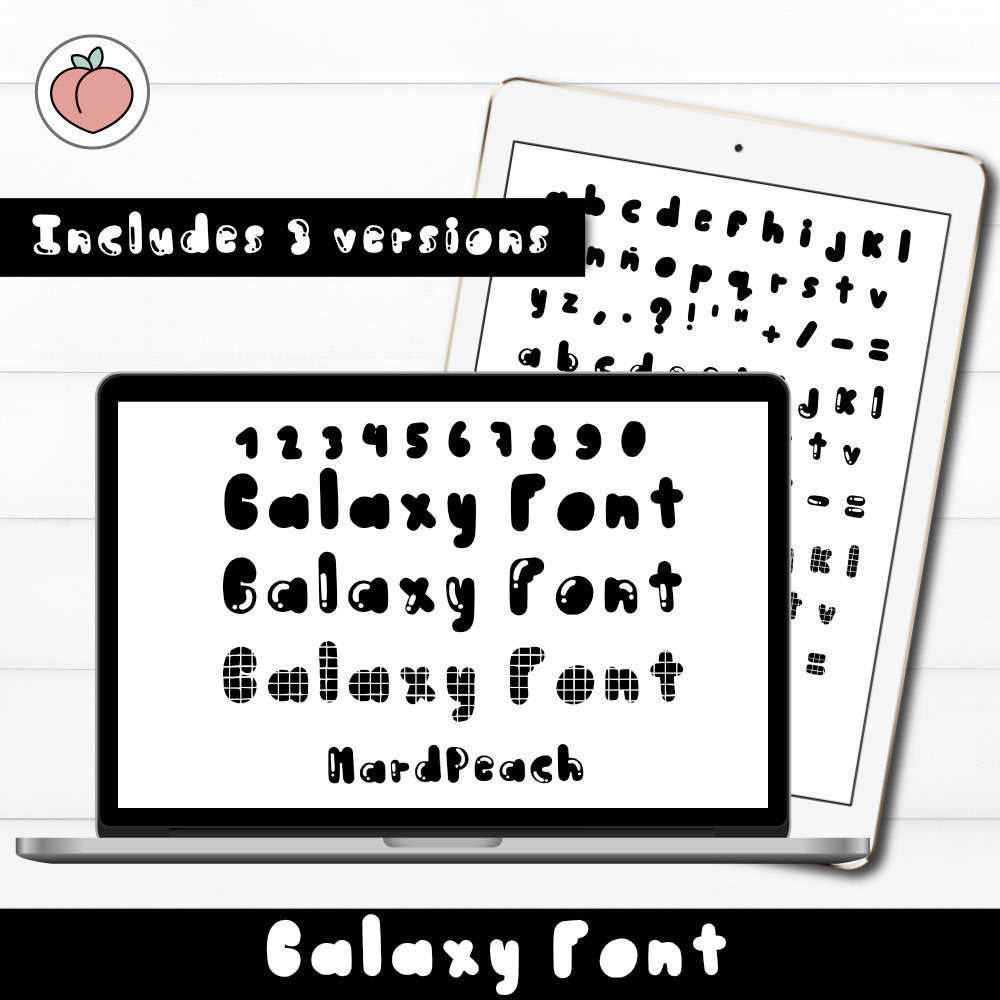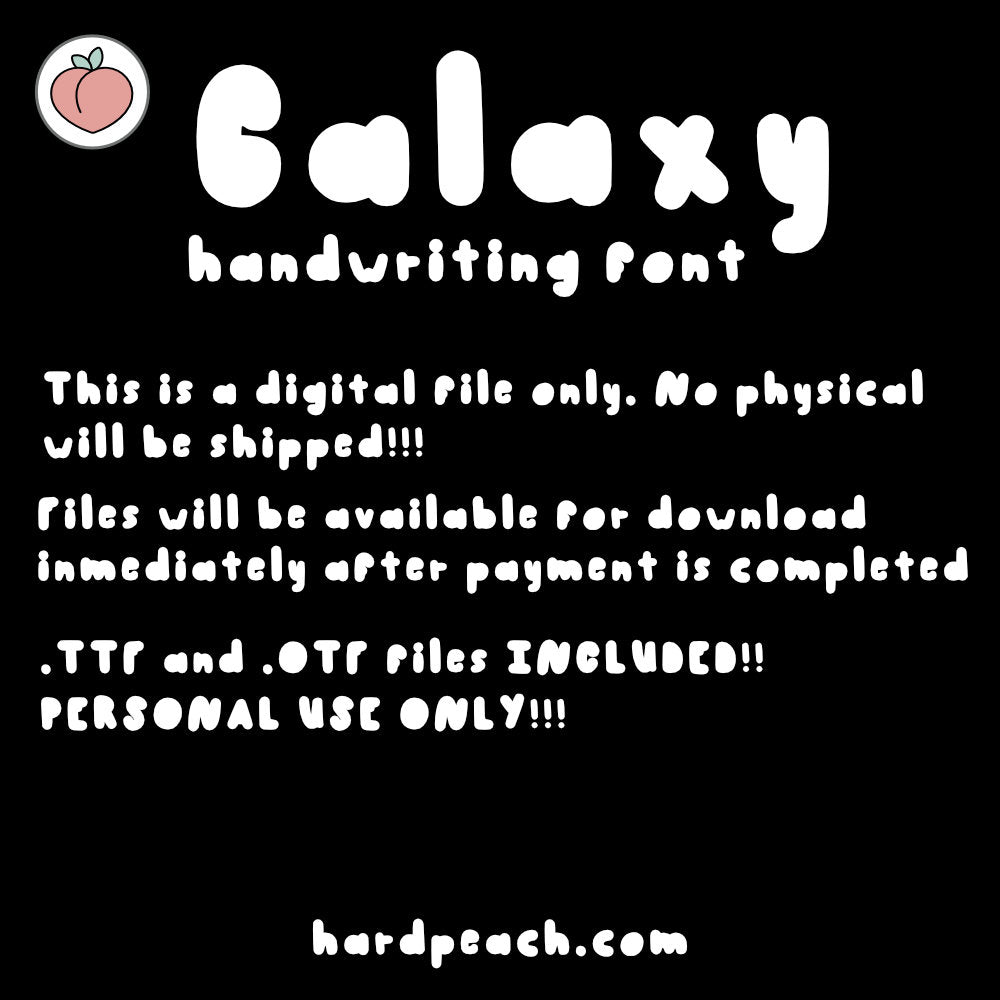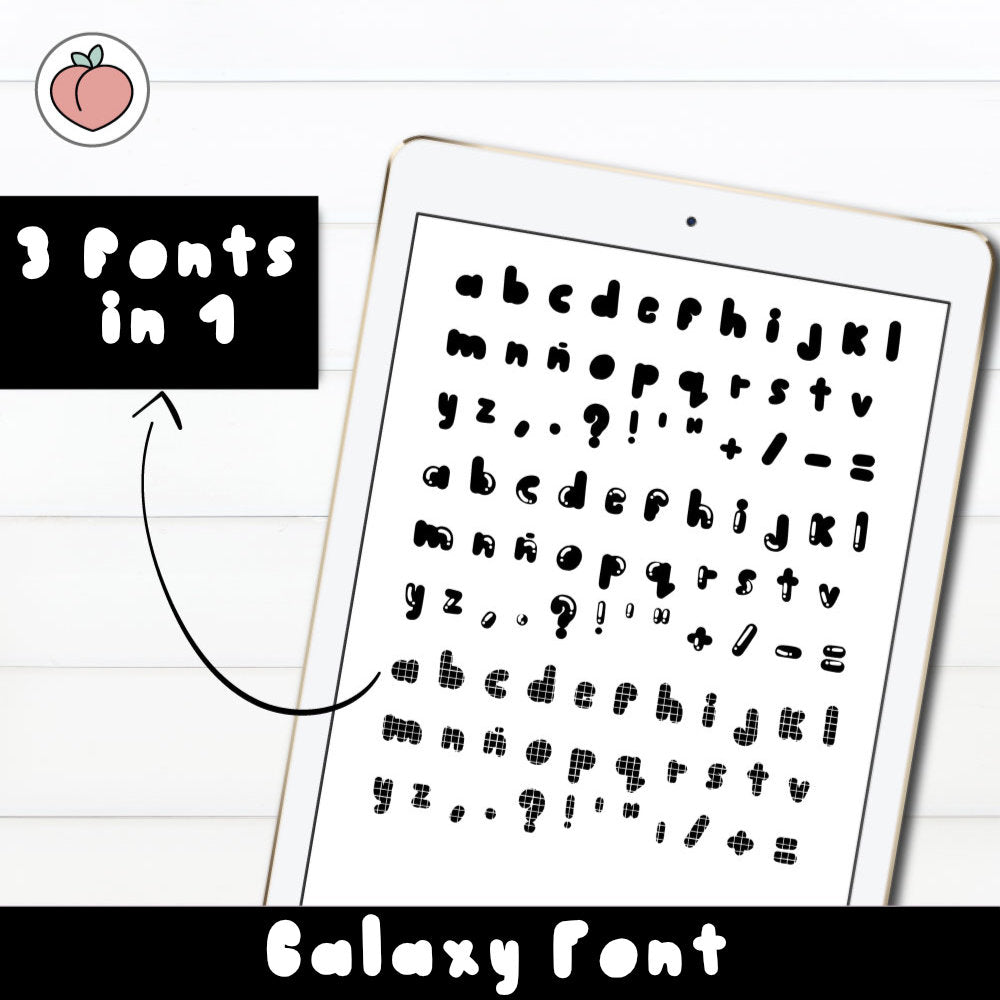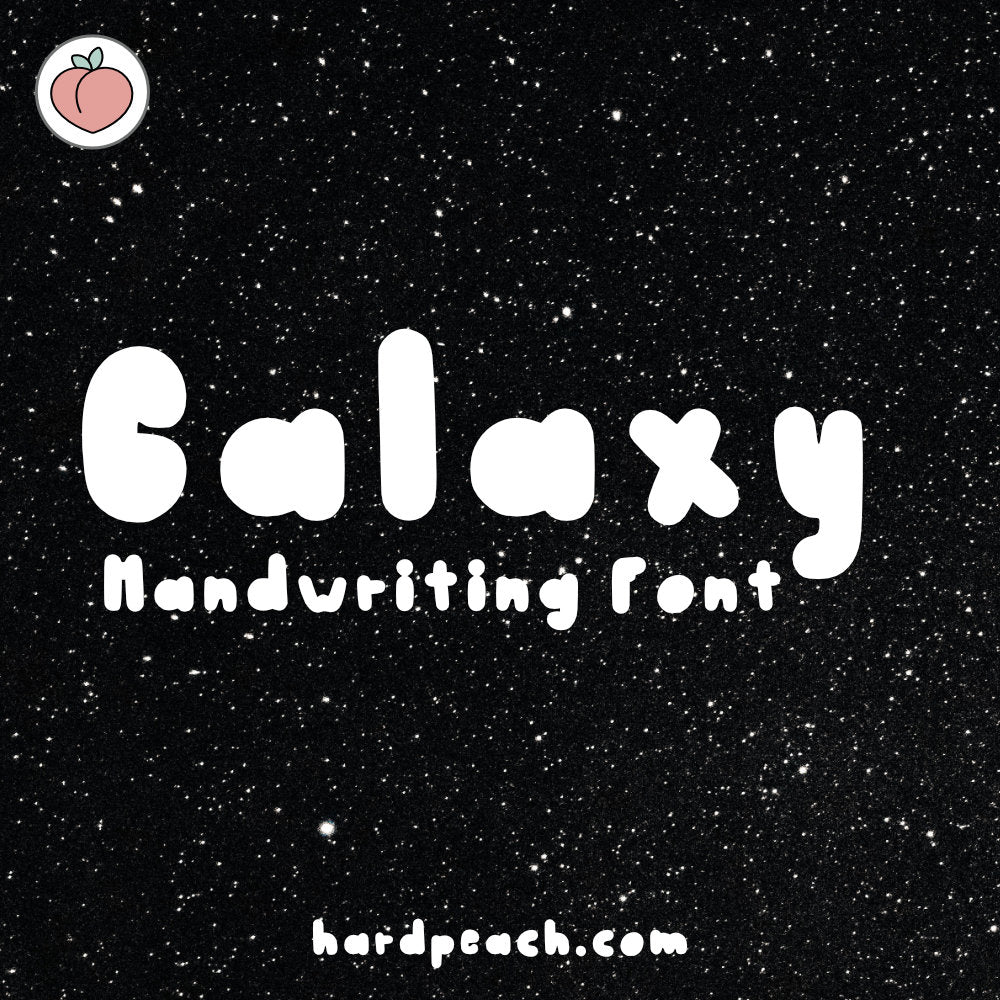
GALAXY HANDWRITTEN FONT
Fuente manuscrita Galaxy para todas tus notas, títulos y Bullet Journal. Esta tipografía le dará un toque especial y personal a tus escritos.
Esta fuente está diseñada en español e incluye todos los caracteres principales: mayúsculas, minúsculas, números, vocales con acentos (español) y algunos signos esenciales. Al estar en español, no incluye algunas acentuaciones de otros dialectos o idiomas.
Esta fuente incluye los siguientes caracteres:
• Alfabeto de la A a la Z
• Números del 0 al 9
• Los signos de puntuación más utilizados
• Signo de interrogación y exclamación
• Versión en negrita
• Versión en cursiva
¡Añade un toque personal y estilizado a tus proyectos con la fuente Galaxy!